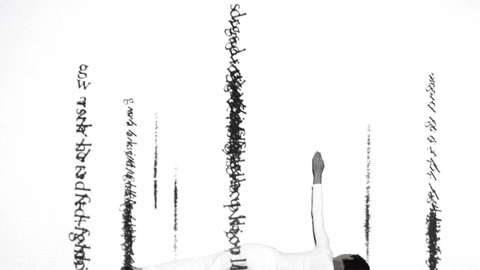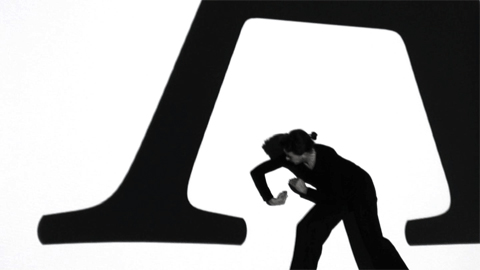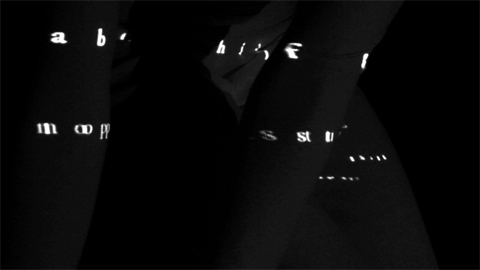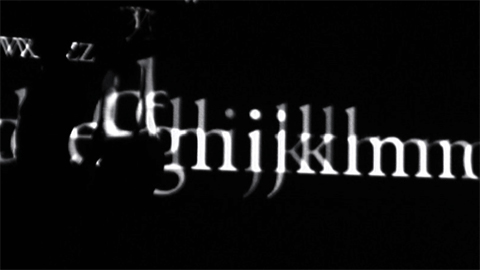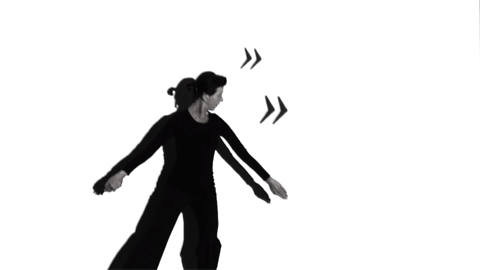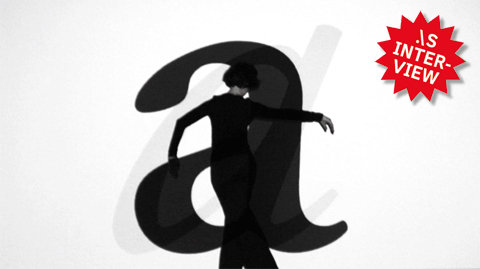
Mit animierter Typografie & Tanz arbeitet Conny Schwark im dreidimensionalen Raum und legt den Schwerpunkt auf individuelle Bewegung. Sie projiziert typografische Elemente in den Raum, spielt mit Licht und einer Tänzerin. Das Zusammenspiel schafft eine ungewohnte, visuelle Sprache.
Conny Schwark setzt sich in ihrer Diplomarbeit das Ziel, animierte Typografie mit Körperbewegung zu verbinden. Auf experimentelle Weise erkundet sie die Beziehung von Typografie, Körper und Bewegung und geht der Frage nach, welche Bildwelten durch deren Kombination entstehen. Sie arbeitet im dreidimensionalen Raum mit einer Tänzerin, einem Beamer und animierten, typografischen Projektionen. Conny Schwark entwickelt einzelne Projektionen zu den typografischen Elementen Buchstabe, Wort, Satz, Zeile und Spalte. Die Tänzerin reagiert mit ihren Bewegungen auf die animierten Projektionen. Starre Typografieregeln wirken im Raum und treten in Dialog mit Bewegung und Licht.
Wie die Fontänen eines Springbrunnens spritzen die Zeilen nach oben, um sogleich wieder von der Schwerkraft nach unten gezogen zu werden. Die Buchstaben fallen in der Zeile zusammen, plätschern im Takt der Musik an den unteren Bildrand. Die schwarzen Zeilen bespielen die liegende, weiss gekleidete Tänzerin. Ihr Arm gesellt sich zwischen die Buchstabenfontänen. Alles ist im Fluss. Die eingesetzten Elemente sind bekannt: Schwarze Schriftzeichen, aufgereiht auf einer Zeile, weisser Untergrund.
Es entsteht eine Bildwelt, in der sich Tänzerin und Projektionen ergänzen, voneinander abgrenzen, miteinander harmonisieren oder sich bewusst stören. Aus diesen visuellen Untersuchungen sind Videosequenzen entstanden, die als Komposition auf http://www.zwischendenzeilen.ch/movie.html zu sehen sind. (Pressetext)
Diplomarbeit 2007: Zwischen den Zeilen
Slanted: Kannst Du uns eine kleine Beschreibung Deiner Arbeit geben?
Conny: Es geht um die experimentelle Untersuchung von animierter Typografie & Tanz. Im Mittelpunkt steht die Beziehung von Typografie, Körper und Bewegung. Ich habe mir die Frage gestellt, welche Bildwelten durch deren Kombination im Raum entstehen.
Slanted: Warum hast Du diese Arbeit gemacht? Wie bist Du auf die Idee gekommen? Was steckt dahinter?
Conny: Es hat alles damit begonnen, dass ich ein Hintergrundbild für eine Bühnenperformance gestalten wollte. Schnell wurde klar, dass es Momente gab, die nur live wirken, und solche, die im Video besser zur Geltung kommen. So hat sich das Ganze dann entwickelt. Nebst der Diplomarbeit als Videokomposition, in der die wichtigsten Sequenzen zusammengestellt sind, wurde auch eine Performance daraus, die im Februar nochmals aufgeführt wird.
Slanted: Was möchtest Du mit Deiner Arbeit erreichen/aussagen?
Conny: Ich wollte eine visuelle Sprache erarbeiten, die mit Bewegung zu tun hat. Es fasziniert mich, wenn ein Körper durch Bewegung zu einer Möglichkeit wird, etwas auszudrücken. Und wenn die Bewegung von animierter Typo ebenfalls einen Ausdruck hat, und nicht nur Aufmerksamkeit erregt, ist das für mich ein wichtiger Mehrwert.
Slanted: Wie/Wo wäre die ideale Anwendungsweise?
Conny: Die Videokomposition sehe ich als Denkanstoss und die daraus entstandene visuelle Sprache als mögliche Form, passende Inhalte zu transportieren.
Die Perfomance werden wir wiederholt aufführen.
Slanted: Arbeitest Du eher darauf los oder gibt es lange Konzeptionsphasen?
Conny: Ich stecke mir gern ein Feld ab, indem ich mich dann frei bewegen kann, um auf Ergebnisse zu reagieren und eine stimmige Lösung zu erarbeiten.
Slanted: Wie lange hast Du an Deinem Werk gearbeitet?
Conny: Im Januar '07 haben die ersten Proben mit der Tänzerin begonnen und bis Ende September '07 war es dann soweit.
hoffentlich gabs bei diesem projekt hier wenigstens auch sekt...
Die Arbeit an sich sieht aber ganz interessant aus.